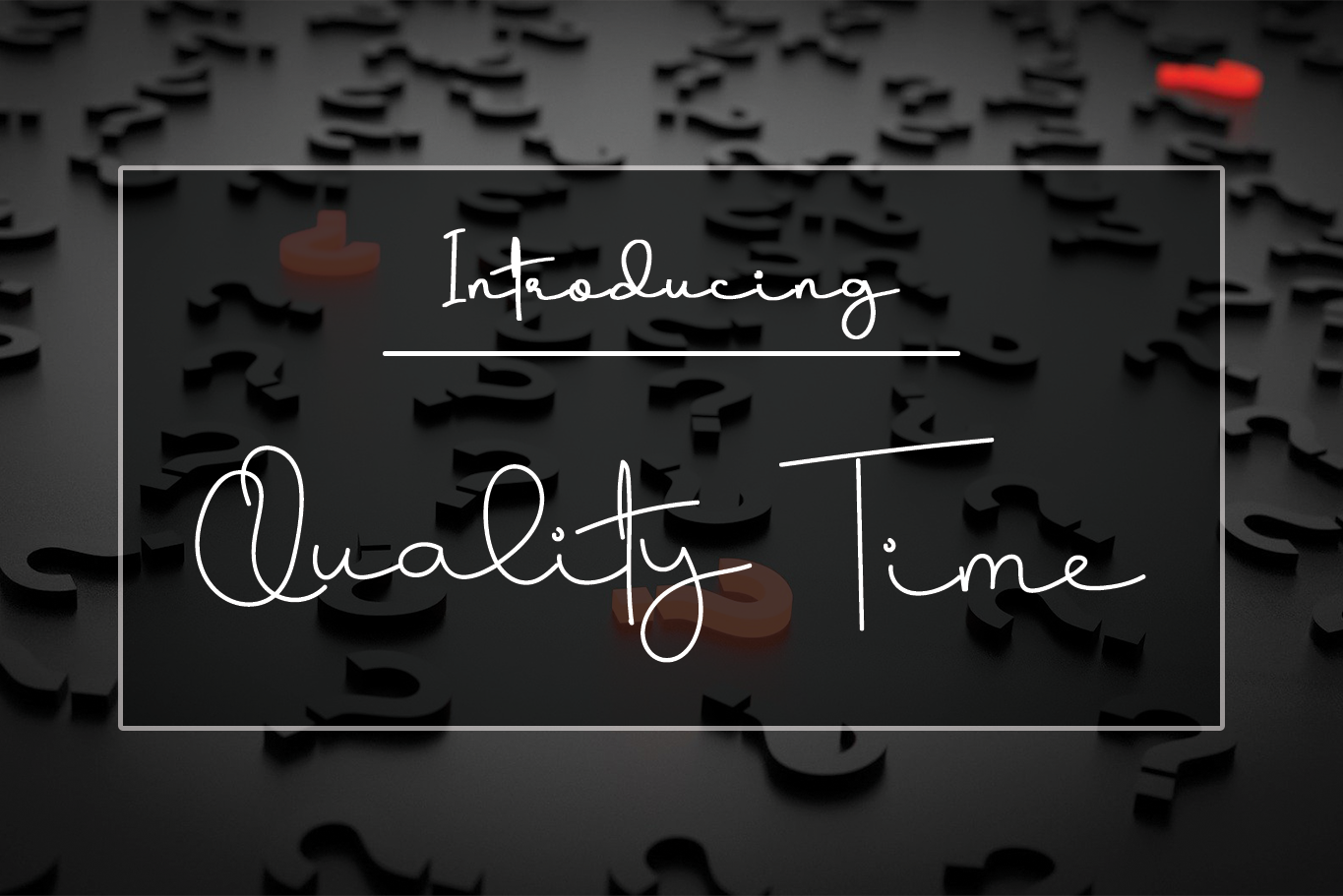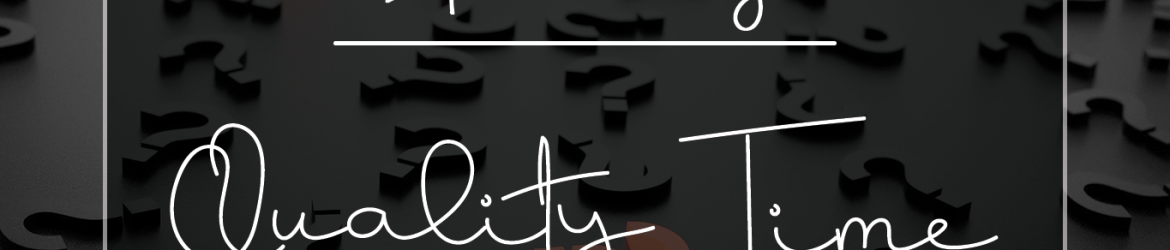
Agora está aqui uma descrição para a página de download da fonte ‘Quality Time Font’, para categorias que incluem logotipos, identidade visual, convites e materiais de decoração, designs de casamento e publicações nas mídias sociais. A fonte é delicada e elegante, perfeita para quem deseja um ar sofisticado em seu trabalho gráfico. Esta font foi criada pelo designer Erik Studio, famoso por suas fuentes cuidadosamente desenvolvidas que combinam classe com modernidade. Se você está procurando uma font que não apenas seja de alta qualidade, mas também uma adição elegante a qualquer projeto visual, então ‘Quality Time Font’ é sem dúvida o seu escolhido. Sinta-se à vontade para explorar e encontrar as possibilidades criativas desta fonte única.